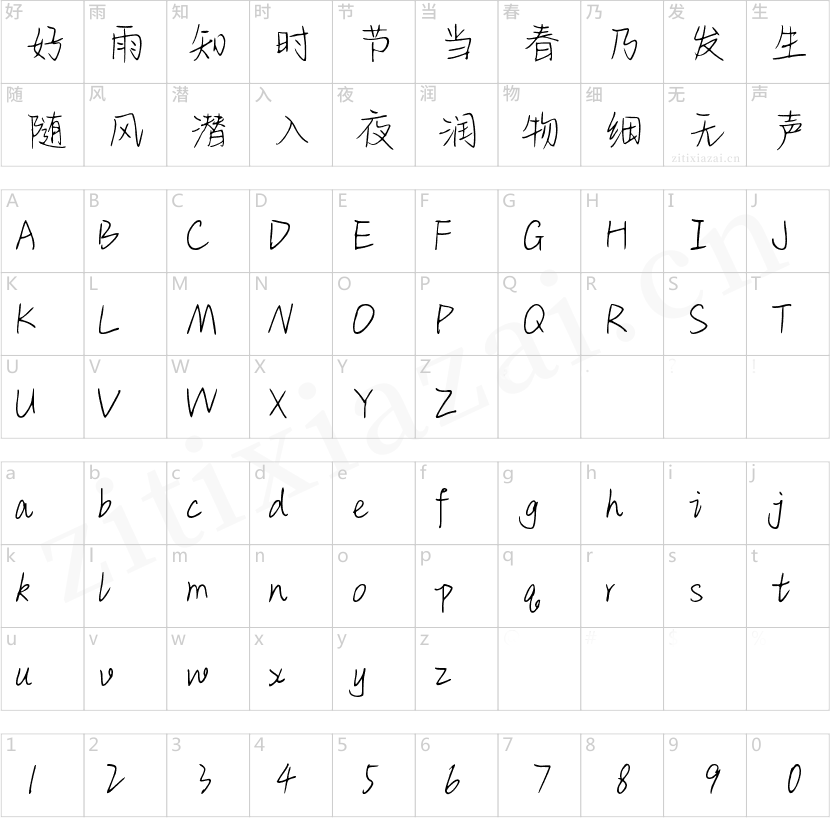
Aa诗经里的情诗
Aa诗经里的情诗,这款字体结构工整、笔画清晰,兼顾美观与易读性,适用于标题、正文、海报、包装、LOGO 等多种场景。字形优雅稳定,风格百搭耐看,适配日常排版与创意设计,让文字呈现更舒适、更具质感。Aa诗经里的情诗一笔一画,皆是细节,以均衡的比例、流畅的线条打造舒适视觉体验,字形端正大气,风格简约现代。无论是商业设计、品牌宣传还是日常排版,都能轻松驾驭,让文字更有格调与力量。Aa诗经里的情诗字体下载。
Aa诗经里的情诗字体
Aa诗经里的情诗是一款非常具有艺术性的字体,它的设计灵感来源于对古典艺术的研究,同时又融入了现代字体设计的元素。字形优美,笔画粗细变化自然,给人以大气、典雅的感觉。Aa诗经里的情诗是一款既传统又现代的字体,它的设计充满艺术感,美观大方,实用性也非常强。无论是对于设计师还是对于普通读者来说,都是一种非常不错的字体选择。Aa诗经里的情诗适合用于具有艺术感的场合,比如海报、宣传单张、书籍封面等。由于其字形流畅且具有动态感,也适合用于大量的文本排版,如报纸、杂志等。